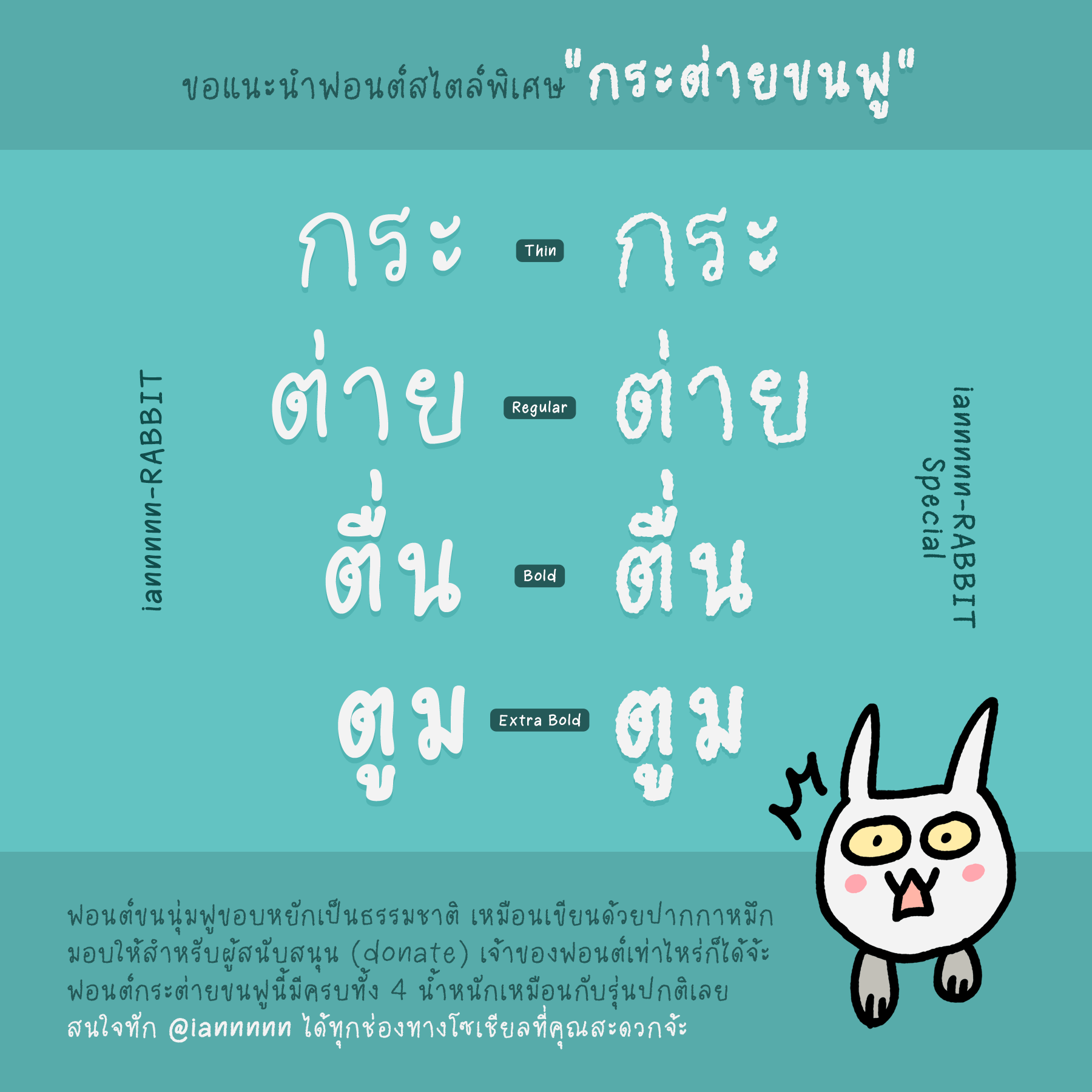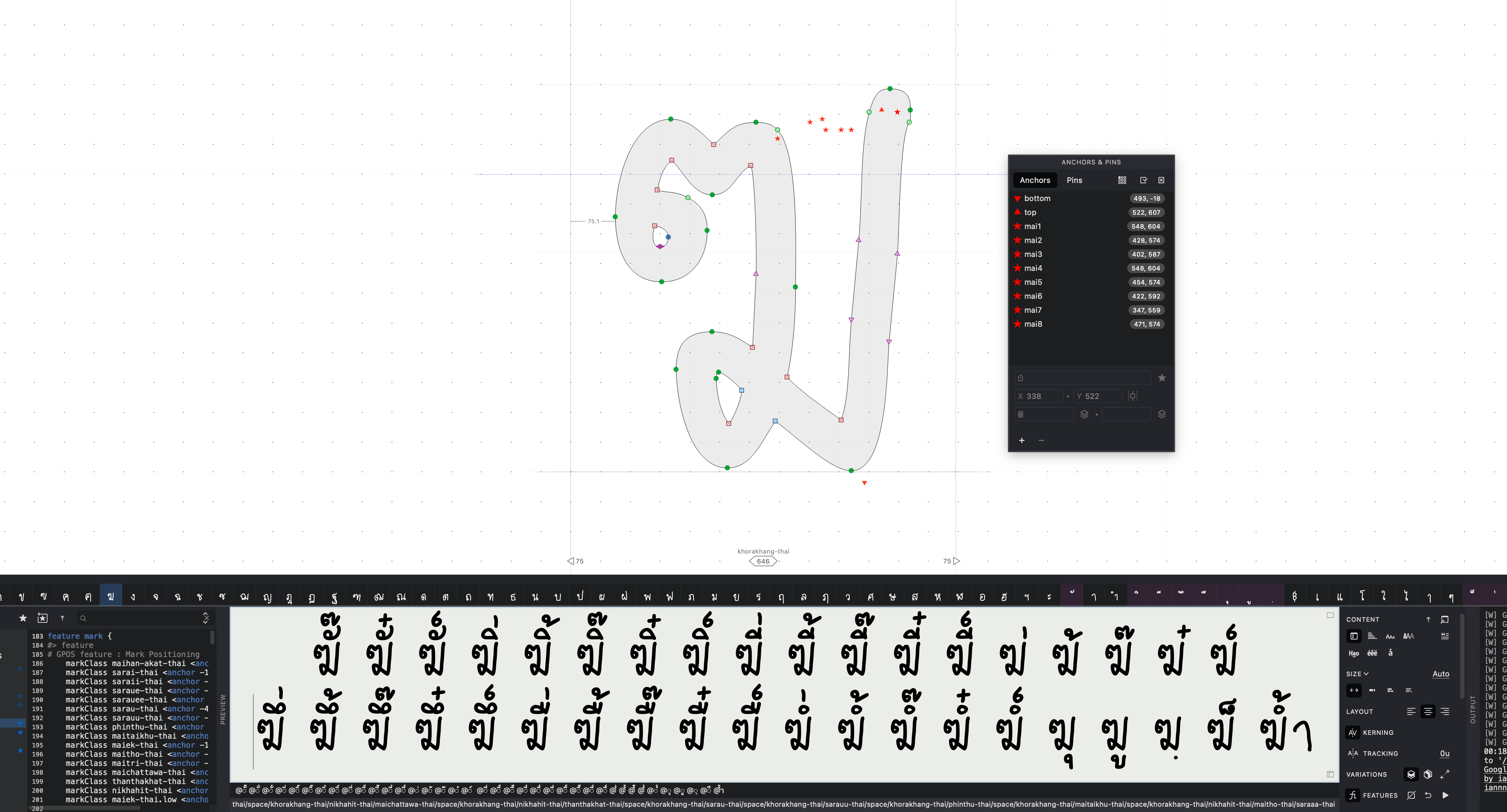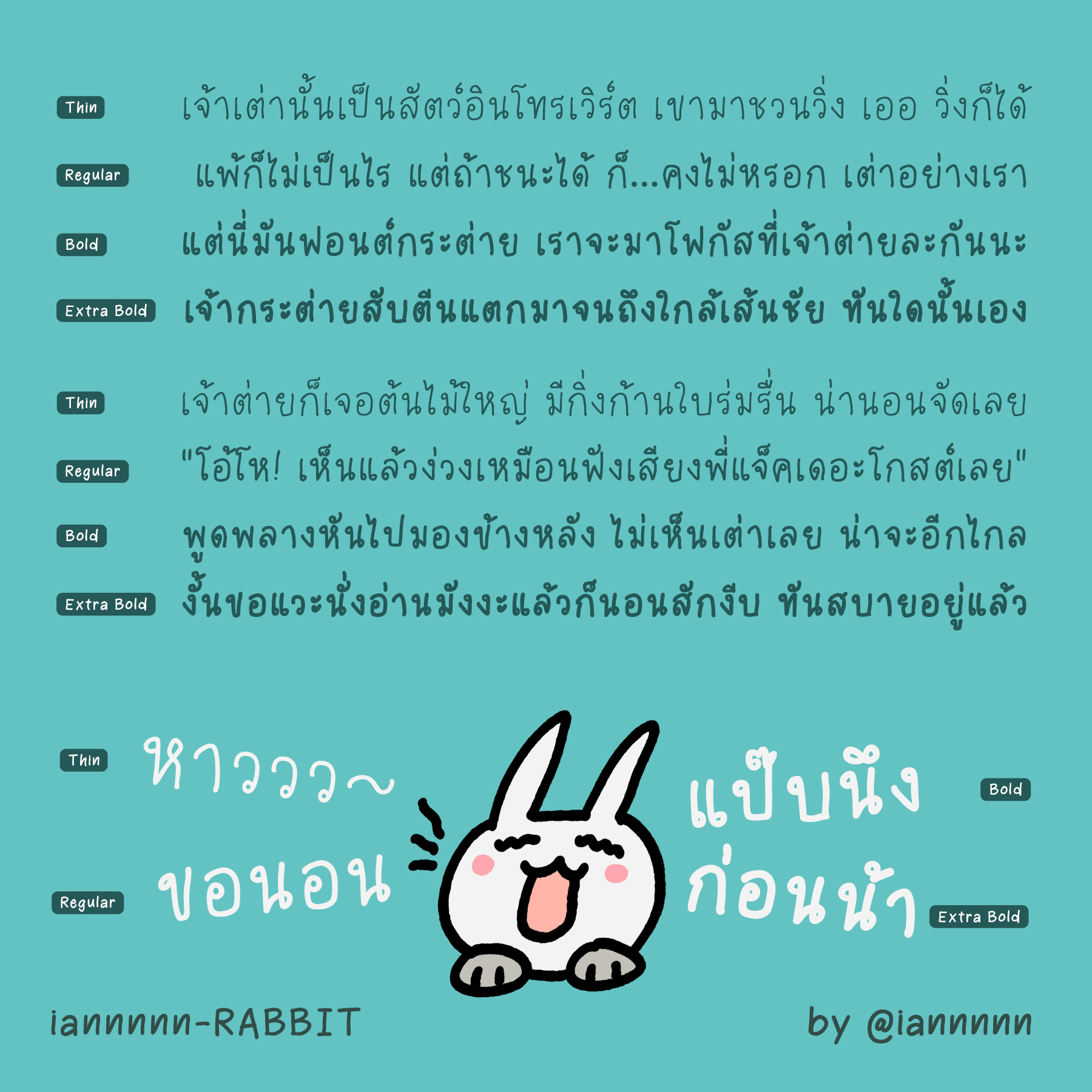
ฟอนต์กระต่าย (iannnnn-RABBIT)
บันทึกการทำฟอนต์กระต่าย (iannnnn-RABBIT)
เพิ่งเริ่มทำตะกี้ โดยใช้แอปทำฟอนต์ของแอนดรอยด์ ชื่อ Quick Font Creator
ที่อยู่ดีๆ ก็นั่งหาว่าเอ๊ะ ตอนนี้แอนดรอยด์เขามีแอปทำฟอนต์ไหมนะ
อ้าว มี!
เมื่อก่อนเคยมีแอปนึง เคยใช้ แล้ววันหนึ่งมันก็หายไปจากตลาด
และวันนี้เขาก็มีคนทำยี่ห้อใหม่มาให้ใช้อีกครั้ง ใช้ง่ายด้วยนะครับ เขียนๆๆ ก็เสร็จแล้ว
อยากลอง แต่ยังไม่อยากจ่ายเต็ม เลยลองที่ฟอนต์เดียวก่อน เป็นค่าครู
ก็เลยเริ่มเขียนขึ้นเส้นในนั้นง่ายๆ ด้วยลายมือตุปัดตุเป๋
แน่นอนว่าเสร็จในเวลาอันรวดเร็ว (เลยชื่อฟอนต์กระต่าย)
ที่จริงมันควรจะจบเสร็จตอนนั้นแหละ แต่ความโรคจิตก็บังเกิด
เมื่อเอามาเปิดใน Fontlab แล้วพบปัญหามากมายต่ายกอง
นั่งแก้ยุบยิบเหมือนฟอนต์อื่นๆ เขาจนได้
ตอนนี้อยู่ในระหว่างการซ่อม โดยใช้เทมเพลตหลักเป็น iannnnn-TEMPLATE
ยังไงก็ยังจะตั้งใจให้เป็นฟอนต์ที่ทำเสร็จเร็วนั่นแหละ เพราะตอนนี้ไม่มีงานด่วนมาแทรก
แต่ก็ขอเวลาจ้ำจี้จำไชอีกหน่อยละกัน มันจะได้อยู่ไปนานๆ
(ตอนทำ iannnnnDVD นั่น 15 นาทีก็เสร็จแล้ว คือถ้าพอมันก็พอ เลิกทำได้ ปล่อยเลย
แต่ตอนนี้แก่แล้ว เห็นความผิดพลาดแล้วมันไม่อยากปล่อยจริงๆ บ้าชิบเป๋ง)
หวังว่าคงทันแจกเดือนนี้แหละ แต่คืนนี้พอก่อน
กระต่ายมาแล้วๆๆ
หวังว่าคงทันแจกเดือนนี้แหละ แต่คืนนี้พอก่อน
กระต่ายที่ว่าวิ่งเร็วๆ ปรากฏว่ามัวแต่นอนหลับใต้ต้นไม้ เพิ่งตื่นเอาตอนจะสิ้นปี
ขอเปลี่ยนจากปล่อยเดือนนี้ (ตุลา) เป็นปีนี้ (ธันวา) นะครับ
ใกล้เสร็จแล้ว นั่งค่อยๆ ปรับตำแหน่งสระวรรณยุกต์อยู่ครับ
ได้ชุดสำหรับใส่เป็นเทมเพลตใน Fontlab เผื่อไว้ทดสอบตำแหน่ง Mark ครับ
ตอนนี้เกลาพยัญชนะไทยเกือบหมดแล้วววว
ตัวอักษรเสร็จ 1 น้ำหนักแล้วครับ
เหลือแก้บั๊ก 1 จุด (สระล่างเจอวรรณยุกต์แล้วออกมาผิดตำแหน่ง)
แล้วก็จะทำน้ำหนักอื่นด้วย
เกือบเสร็จแล้ว เหลือจัดช่องไฟอีกนิดเดียว :33:
สรุปว่าบั๊กเมื่อคืนคือ ติดที่ลืมใส่ _top ใน Anchor ของพวกวรรณยุกต์ครับ
ทดสอบสระวรรณยุกต์อย่างเจ้มจ้น
นี่นะๆ
ชุดทดสอบสระบนล่าง + วรรณยุกต์ครับ ขอบคุณการมีอยู่ของ Gemini